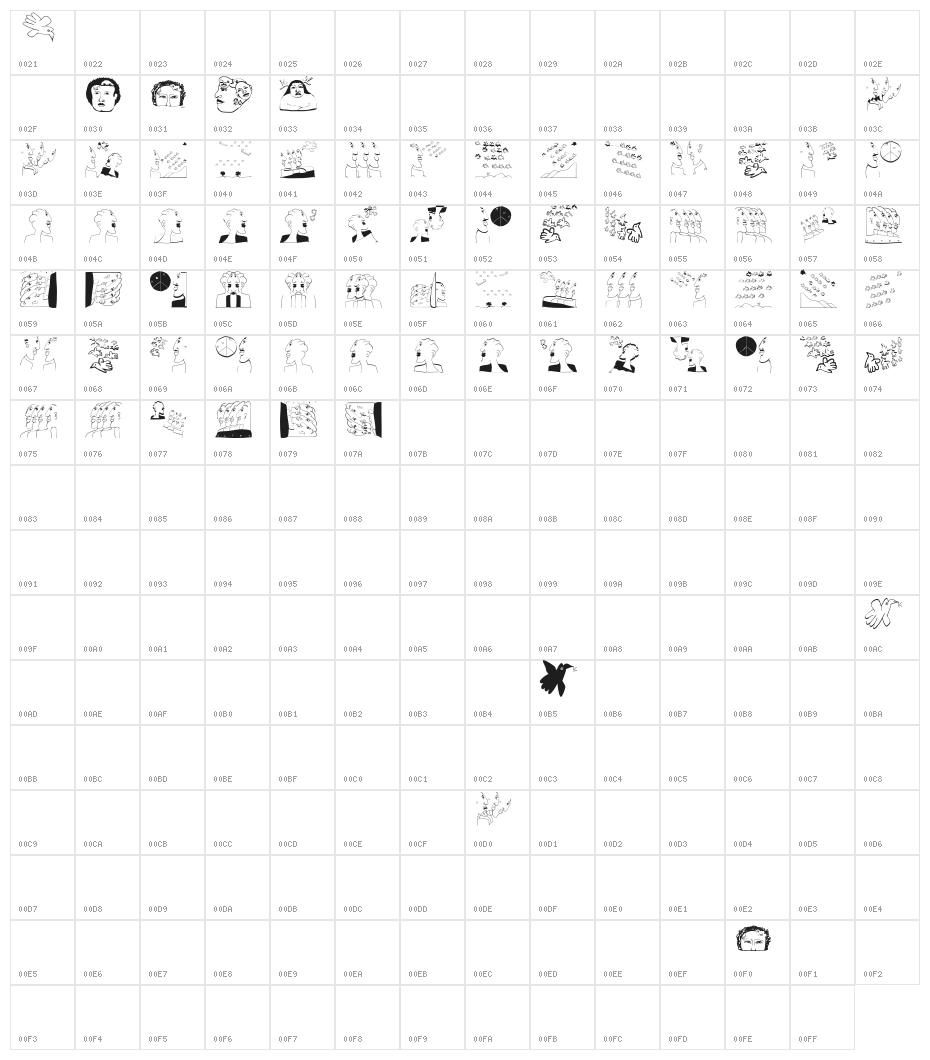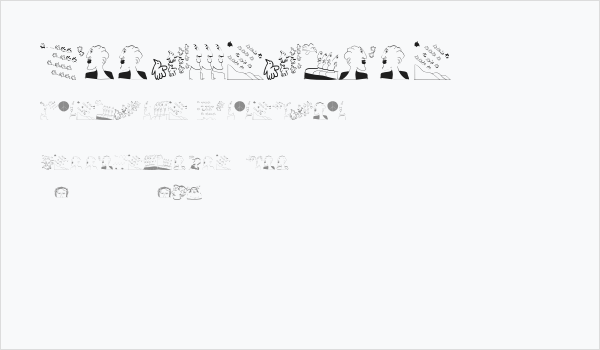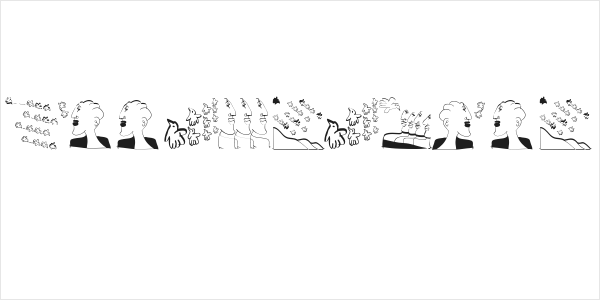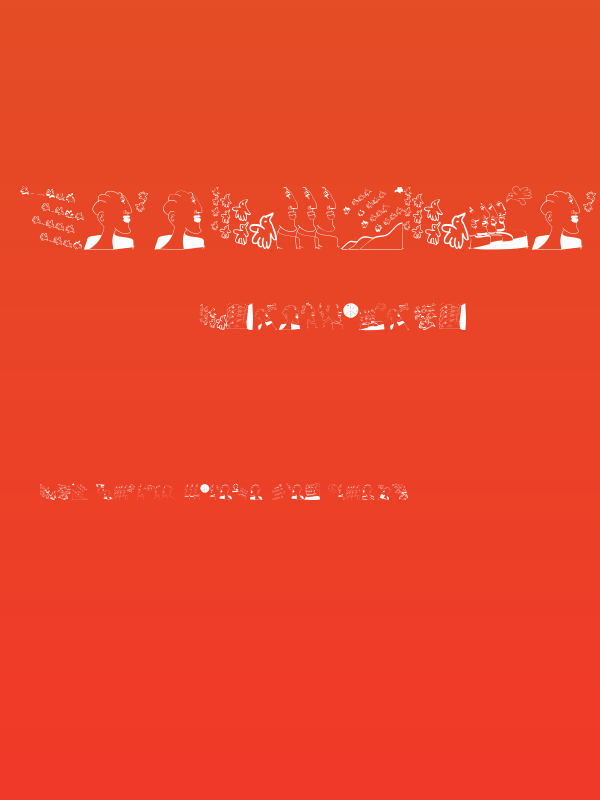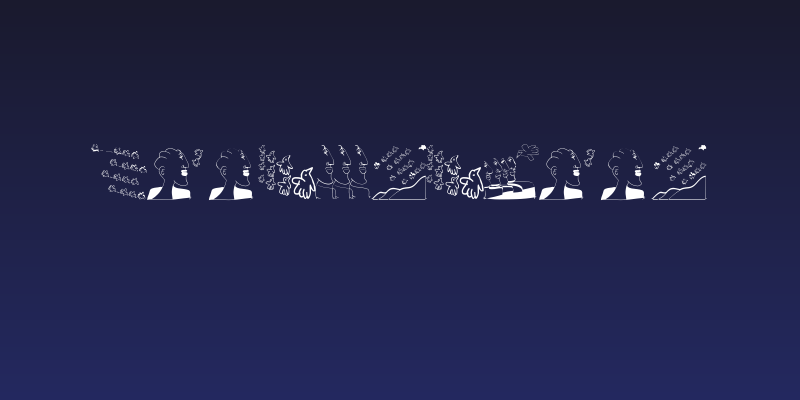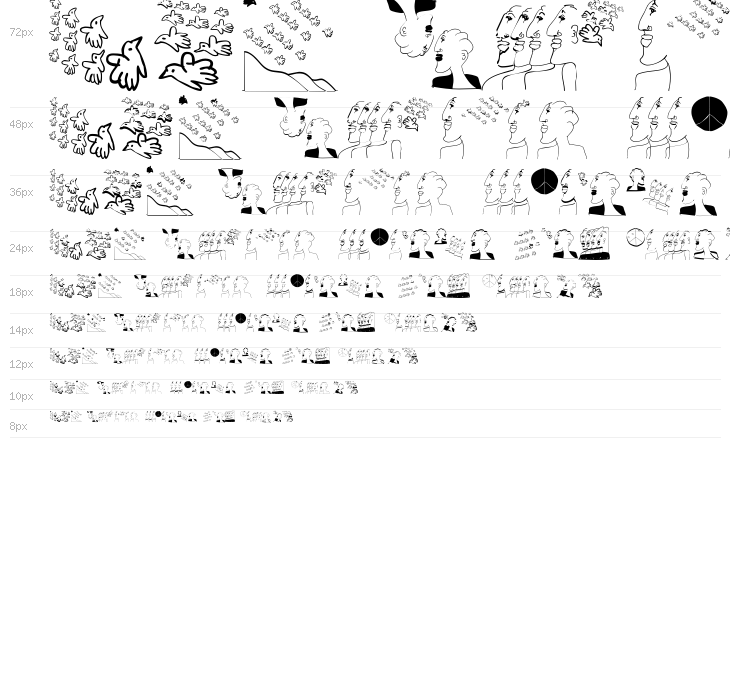
FontBetaOne Font
| Gesamtstil | Decorative, Artistic, Whimsical |
| Anwendungsfall | Logos, Posters, Art projects, Editorial headlines |
| Vorgeschlagene Projekte | Children's books, editorial illustrations, creative posters, album covers, art zines, branding for playful or artistic projects. |